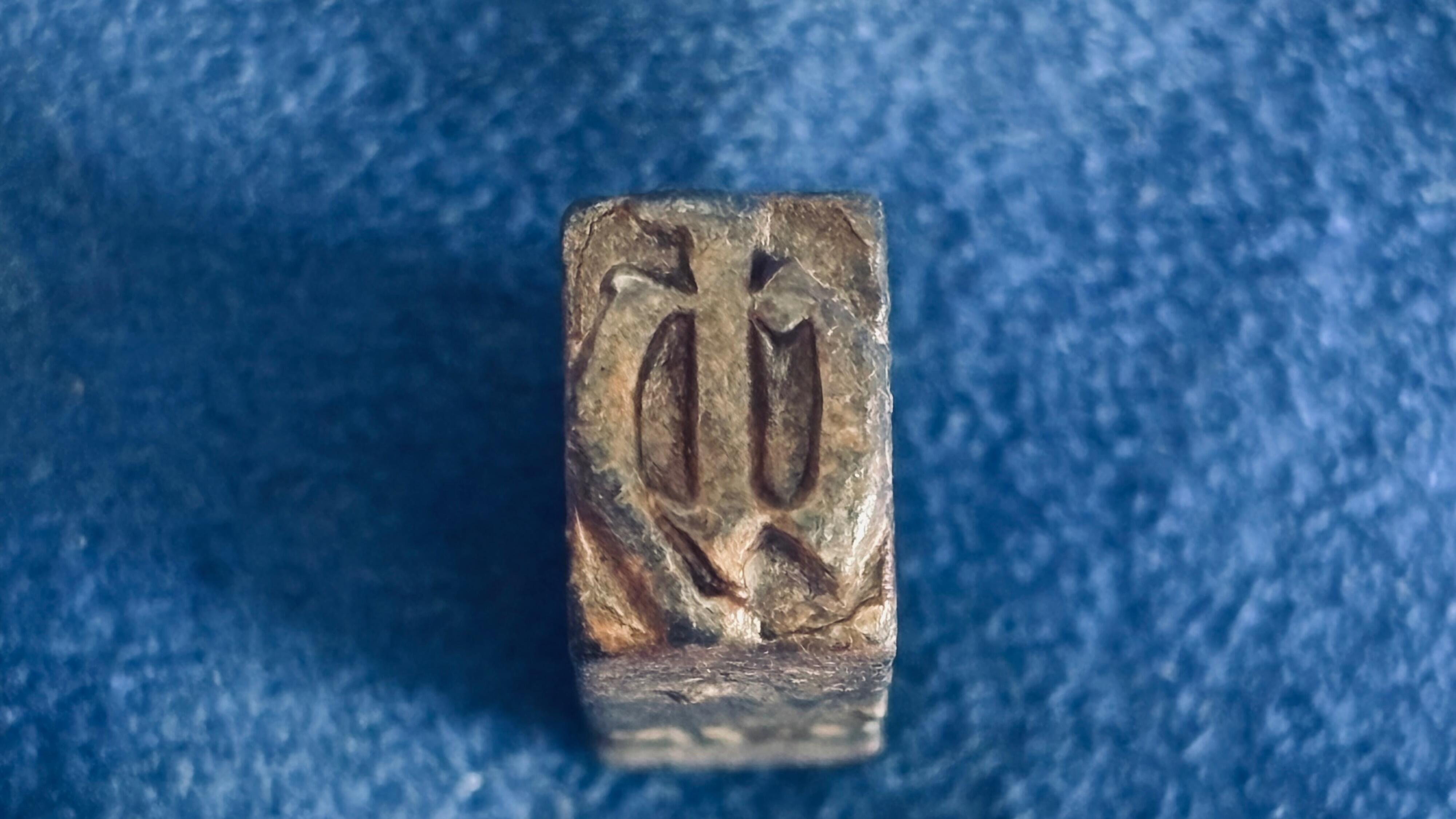
Im Erdboden gefundener Bleisatz in Fraktur
Vielen Dank für die Aufnahme in diesem Forum. Ich habe in Berlin in der Erde einen Bleisatz gefunden. Er muss auf Grund der Lage ca. 150 - 250 Jahre dort gelegen haben. Durch immerwährende Nutzung des Bodens als Anbaufläche hat sich das „ch“ leider abgenutzt. Vielleicht habt ihr so einen Fraktursatz schon mal gesehen und könnt ihn genauer bestimmen?
Es passt zumindest gestalterisch zu Frakturschriften der angegebenen Zeitspanne. Genauer wird man das kaum eingrenzen können. Die Gestaltung ist nicht sonderlich charakteristisch, die Details sind verwittert und Schriften hatten vor 200 Jahren auch keine eindeutigen Markennamen wie heute.
Vielen Dank schonmal. Es sind ja schon Ähnlichkeiten zur späteren Senatsfraktur vorhanden. Vor allem die einfach gehaltenen Serifen im Gegensatz zum üblichen Fraktursatz